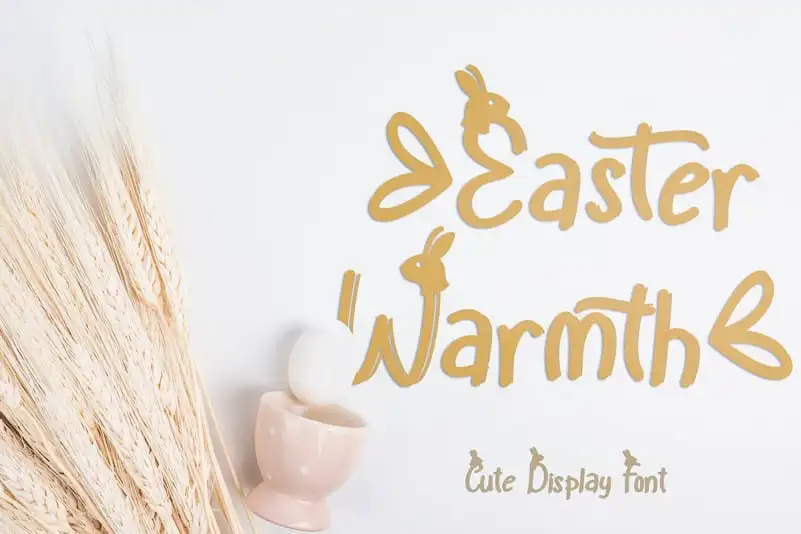
Easter Warmth Display Font – Download Grátis
Esta fonte é chamada “Easter Warmth Display Font”. Ela é tão fácil de usar que tornará suas letras lindas e encantadoras. Com este design único e fofo, ela se destaca para celebrar a celebração da Páscoa. Não apenas isso, mas esta fonte também pode ser usada em diversas outras aplicações. Como criar selos para livros, mangá, títulos de filmes, animações, promoções, entre outros. É perfeitamente adaptável à sua necessidade de design criativo, tornando seu trabalho ainda mais atraente e único.